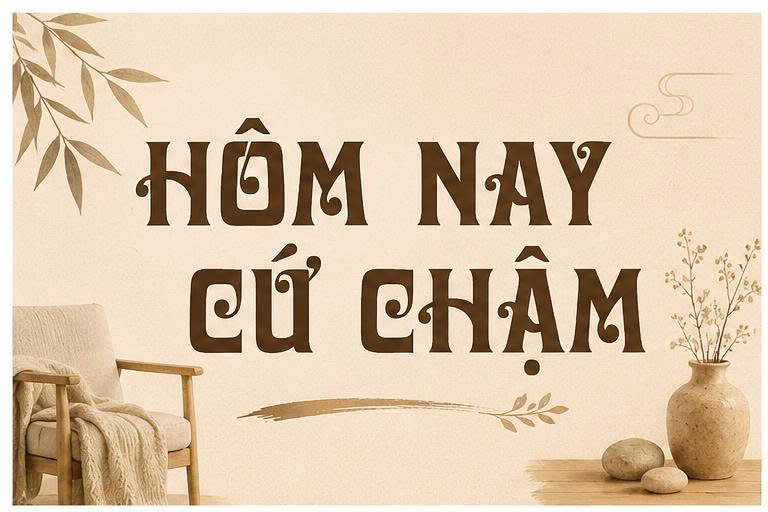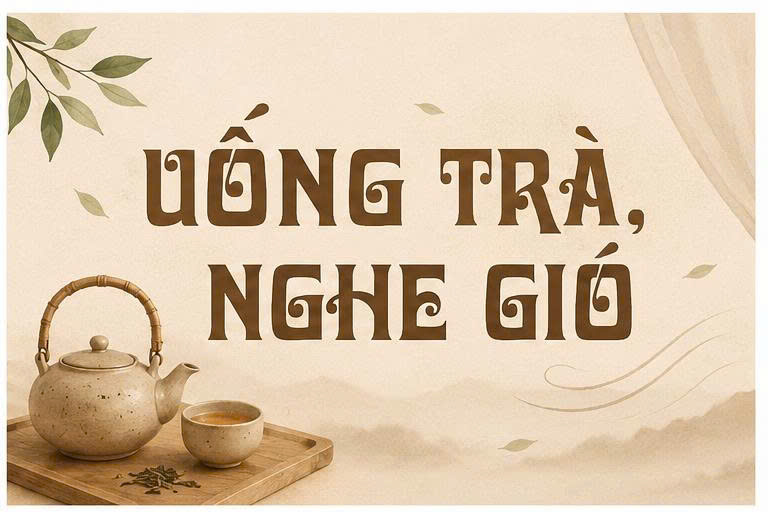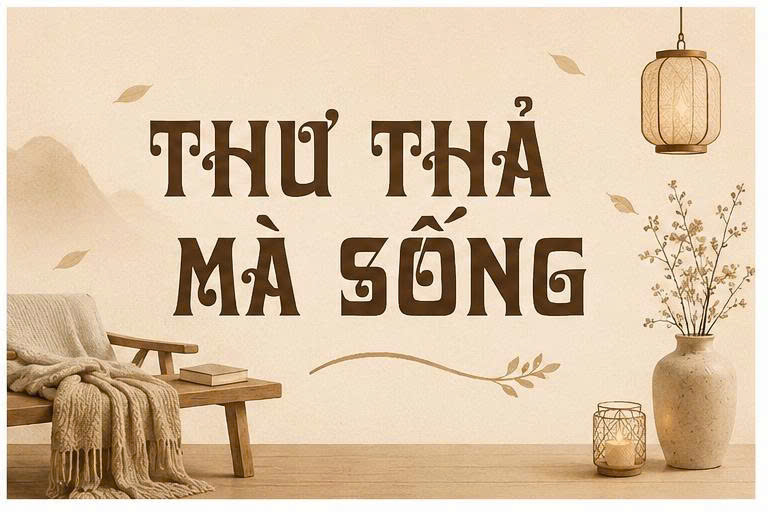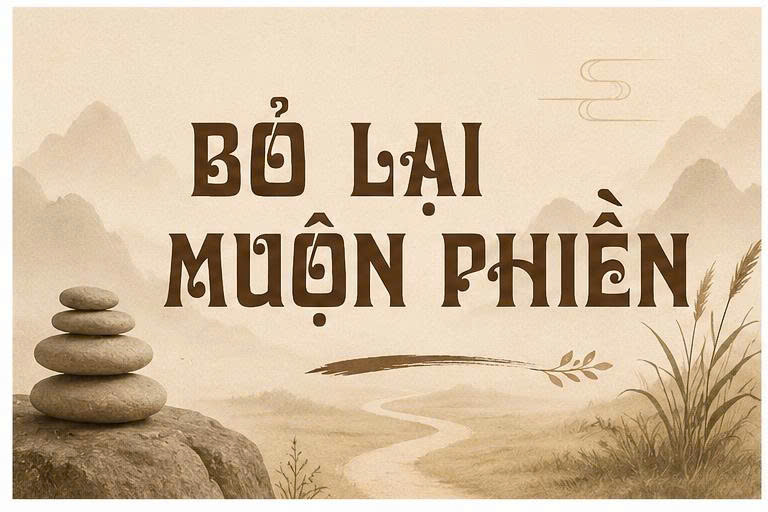
Font Việt hóa UTM Davida là bộ phông chữ thuộc dòng Decorative Serif mang đậm phong cách cổ điển thế kỷ 19, nổi tiếng với những đường nét uốn lượn hoa văn tinh xảo và diện mạo vô cùng quý phái. Với cấu trúc chữ độc đáo, vừa uy nghi vừa bay bổng, UTM Davida là lựa chọn hàng đầu cho các thiết kế tiêu đề, logo cao cấp và bao bì sản phẩm mang hơi hướng hoàng gia hoặc Vintage. Doozypack.vn chia sẻ link tải font UTM Davida chuẩn, giúp bạn sở hữu phông chữ nghệ thuật không lỗi dấu thanh để nâng tầm đẳng cấp cho mọi bản thiết kế.
Đặc điểm thẩm mỹ của font UTM Davida Việt hóa
UTM Davida không chỉ đơn thuần là một bộ phông chữ tiêu đề; nó là một tác phẩm nghệ thuật đồ họa giúp truyền tải thông điệp về sự xa hoa và tinh tế.
Phong cách Victorian cổ điển và sang trọng
Đặc trưng lớn nhất của font UTM Davida Việt hóa là sự kết hợp giữa những nét dọc dày dặn, chắc chắn và các đường cong trang trí uốn lượn cầu kỳ. Cấu trúc chữ gợi nhắc đến phong cách nghệ thuật thời kỳ Victoria, nơi mỗi ký tự đều được chăm chút như một món đồ trang sức. Chính nét đẹp này giúp tiêu đề bản thiết kế của bạn toát lên sự quý phái, rất phù hợp với các thương hiệu về rượu vang, xì gà, hoặc mỹ phẩm cao cấp.
Hệ thống dấu tiếng Việt chuẩn hóa bộ font UTM
Nằm trong hệ sinh thái font UTM nổi tiếng tại Việt Nam, Davida đã được tinh chỉnh bộ dấu một cách tỉ mỉ. Các dấu thanh (sắc, huyền, hỏi, ngã, nặng) được thiết kế mộc mạc nhưng đồng nhất với độ đậm của thân chữ, đảm bảo văn bản tiếng Việt luôn giữ được sự cân đối và nhịp điệu nghệ thuật của font gốc. Việc sử dụng font UTM Davida Việt hóa giúp designer loại bỏ hoàn toàn tình trạng lỗi font khi gõ các từ khóa đặc thù.
Tại sao designer nên chọn font UTM Davida cho thiết kế bao bì Luxury?
Trong ngành thiết kế và sản xuất bao bì tại Doozypack.vn, UTM Davida luôn được ưu ái nhờ khả năng “nâng tầm” giá trị sản phẩm tức thì:
- Tạo dấu ấn thương hiệu đắt tiền: Chỉ cần đặt tên thương hiệu bằng font Davida, bao bì sản phẩm của bạn đã toát lên vẻ lâu đời và uy tín, dễ dàng chinh phục phân khúc khách hàng cao cấp.
- Tính ứng dụng độc bản: Khác với các dòng font Serif phổ thông, cấu trúc trang trí của Davida giúp Logo hay nhãn mác của bạn nổi bật hoàn toàn trên kệ hàng.
- Dễ dàng kết hợp kỹ thuật gia công: Bề mặt nét chữ của Davida rất phù hợp để ứng dụng các kỹ thuật in ấn cao cấp như ép kim vàng hoặc dập nổi 3D.
Ứng dụng của font Davida trong sản xuất bao bì tại Doozypack.vn
Vẻ đẹp quý tộc của Davida mang lại hiệu quả thị giác đặc biệt trên các ấn phẩm thực tế do Doozypack.vn sản xuất:
- Nhãn rượu vang & Xì gà: Nét chữ trang trọng của Davida giúp nhãn sản phẩm toát lên sự truyền thống và đẳng cấp vượt thời gian.
- Hộp mỹ phẩm & Nước hoa: Sự kết hợp giữa font Davida và kỹ thuật ép kim nhũ bạc trên nền giấy Ivory đen tạo nên diện mạo vô cùng cuốn hút.
- Bao bì quà tặng doanh nhân: Dùng cho các câu chúc hoặc tên thương hiệu trên nắp hộp cứng cao cấp để nhấn mạnh sự trân trọng đối với người nhận.